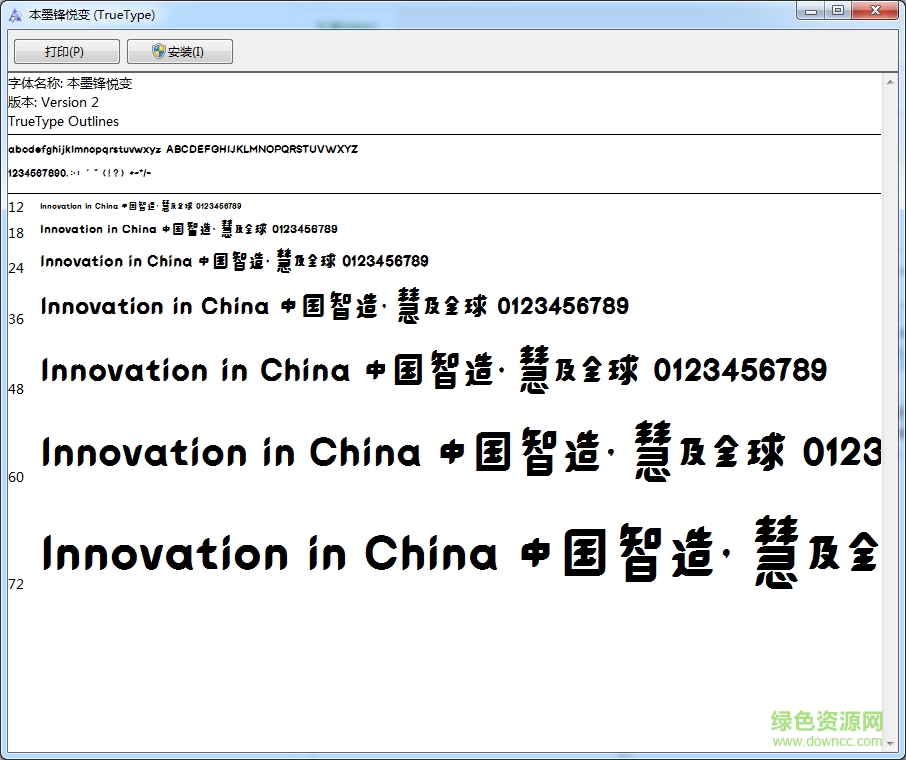
本墨鋒悅變2.0
本墨鋒悅變2.0是一款廣泛使用的電腦字體,字體大小形狀不一極具個(gè)性,支持英文漢子數(shù)字等多種方式輸入顯示??靵?lái)綠色資源網(wǎng)下載體驗(yàn)吧!
本墨鋒悅變字體介紹
本墨鋒悅變字體擁有全新的字體構(gòu)造,讓您的字給人留下更為深刻的印象,有喜歡這款個(gè)性字體的朋友不要錯(cuò)過(guò)了。